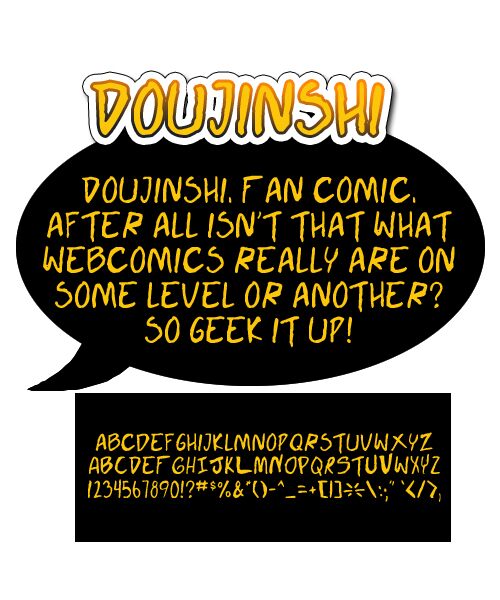
Doujinshi od Shonen Fonts to darmowy krój pisma typu "brush", inspirowany mangą, z surowym, inkrustowanym wykończeniem. Litery wyglądają, jakby zostały namalowane pędzlem – są wysokie, nierówne i lekko poszarpane na krawędziach. Dzięki temu czcionka niesie ze sobą niespokojną energię ręcznie rysowanych efektów dźwiękowych w komiksach i tytułów zinów, unikając przy tym przesadnej schludności.
Idealnie sprawdzi się na nagłówkach plakatów, okładkach komiksów, ulotkach zespołów, grafikach na merch czy przy otwarciach rozdziałów, gdzie ten szorstki, malarski rytm gra główną rolę. Jako darmowy font, Doujinshi świetnie nadaje się również do plansz tytułowych, cytatów czy krótkich znaków brandingowych, ponieważ wielkie litery dają odważny i bezpośredni efekt, nie wyglądając przy tym zbyt sterylnie.